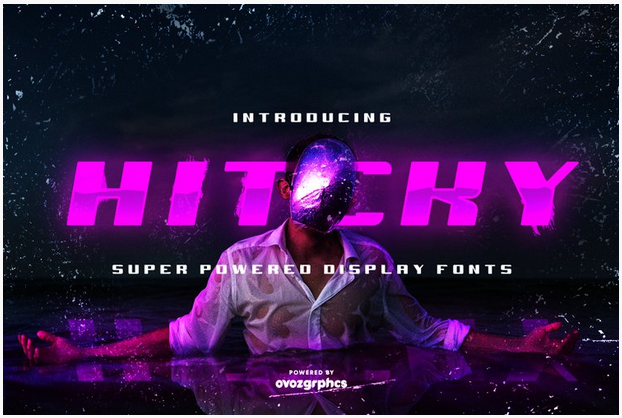
Fontbundles Hitcky super powered display font 2020
[Fontbundles] Hitcky super powered display font (2020)
HITCKY SUPER POWERED DISPLAY FONT - это наш новый элемент, который подходит для логотипа вашей команды или логотипа сообщества.
Отлично подходит для логотипа, наклейки, джерси, пригласительного билета, брошюры и т. Д.